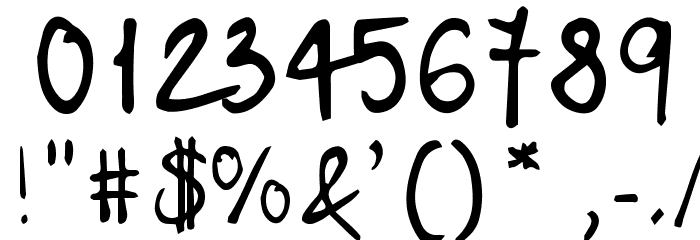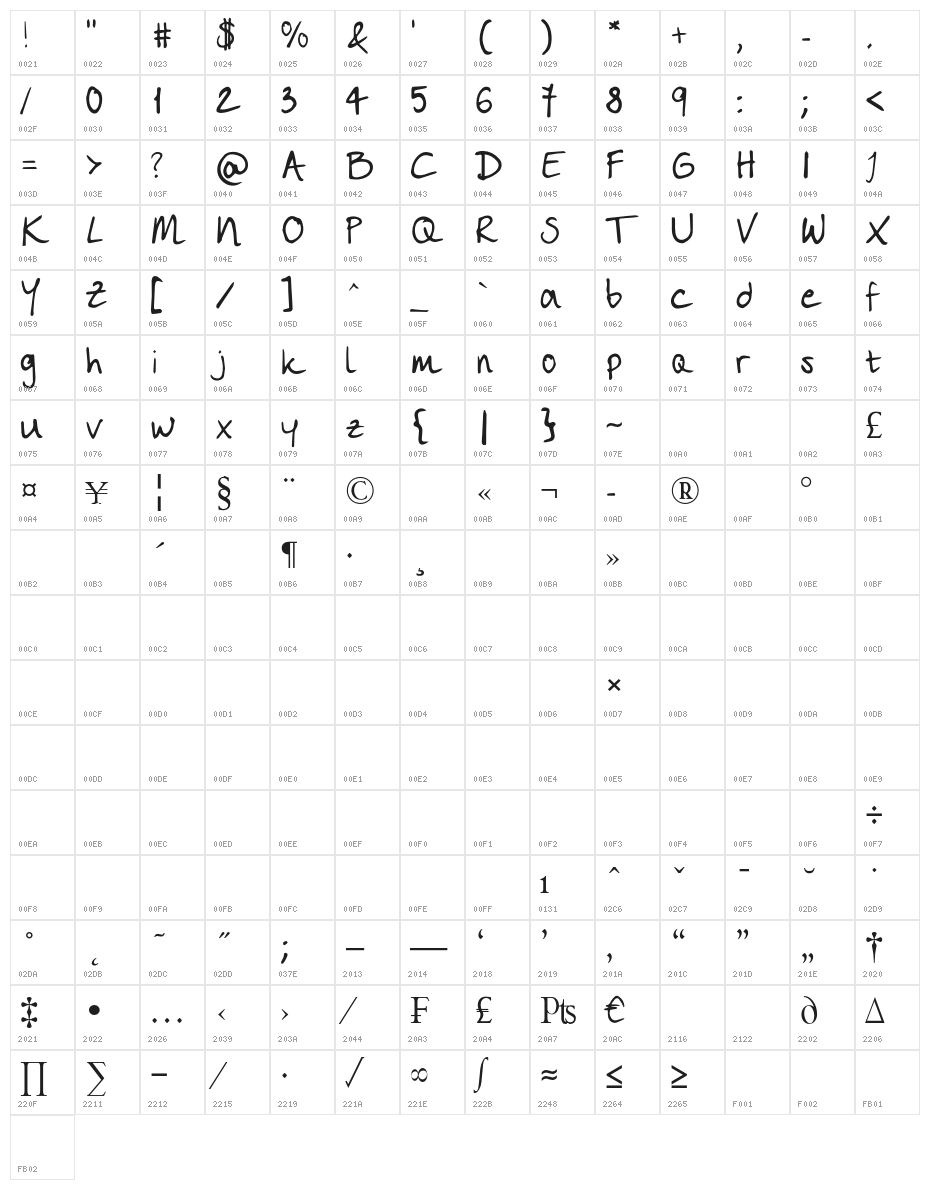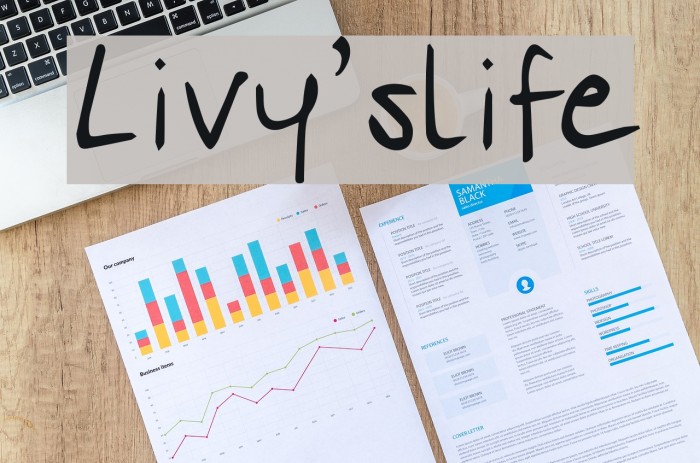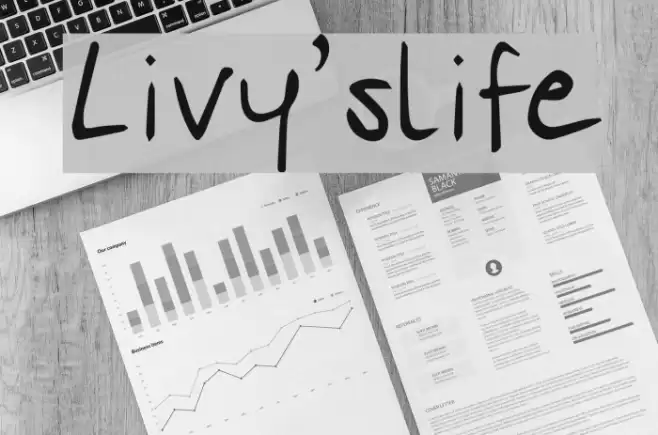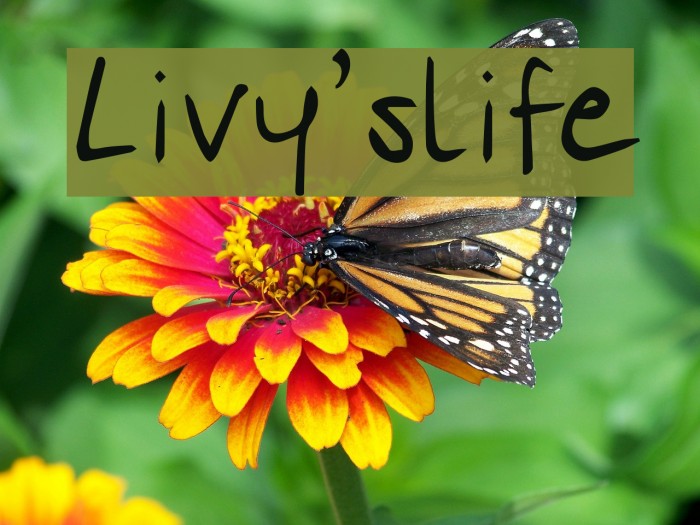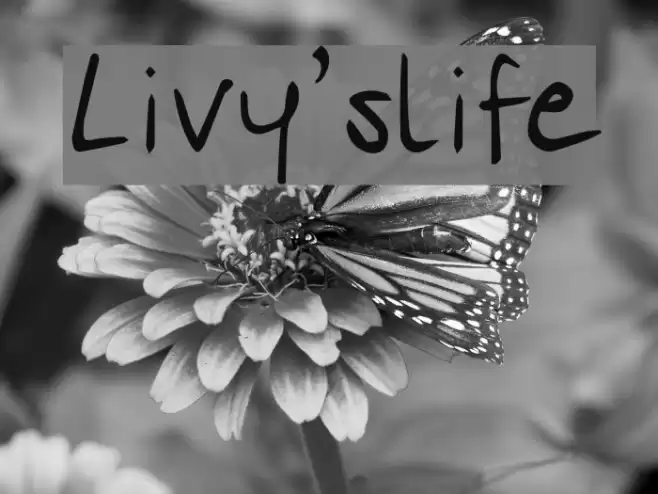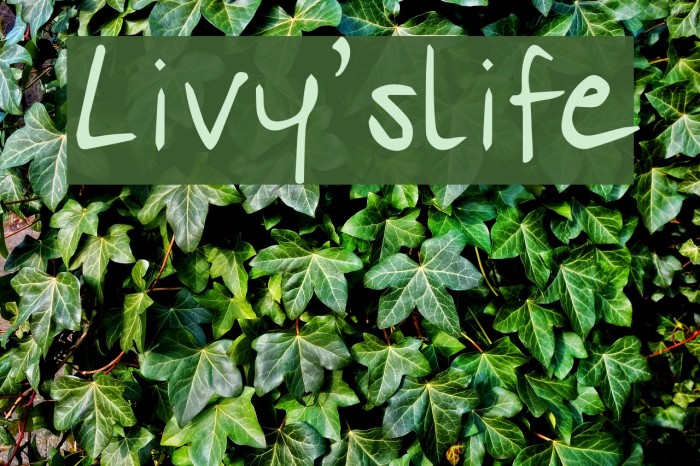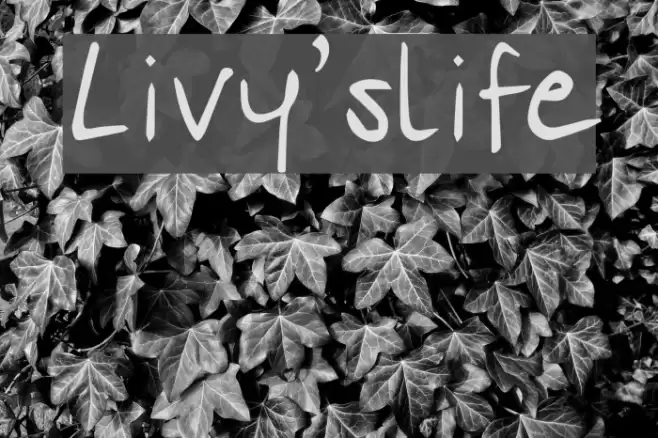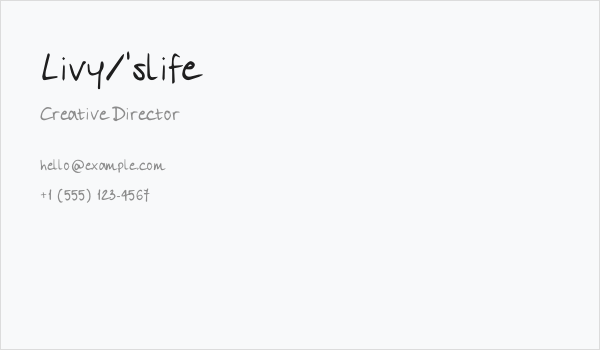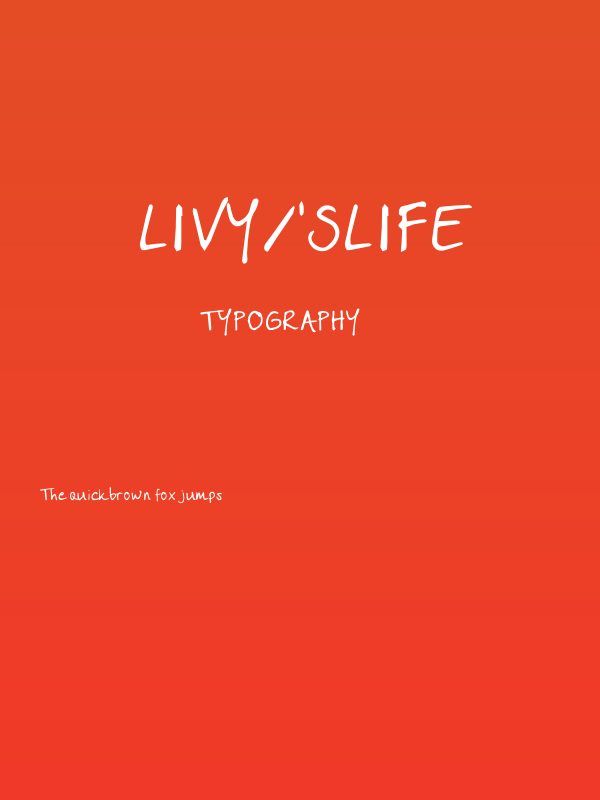
Livy'slife Font
| Caz de utilizare | Headlines, Informal text, Personal projects |
| Proiecte propuse | Ideal for greeting cards, personal blogs, children's books, and informal branding projects. |